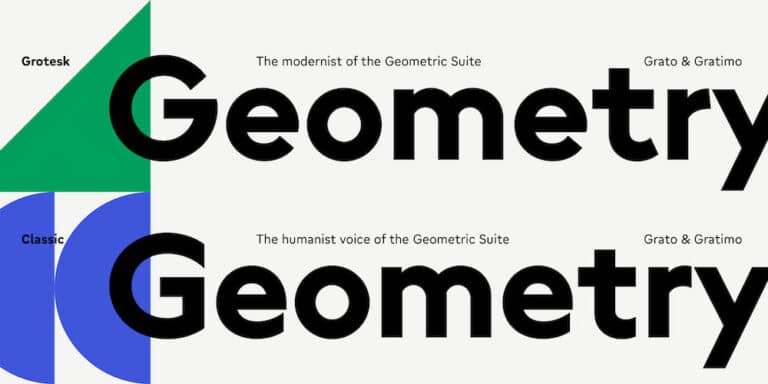
Grato und Gratimo: Serifenlose Großfamilie
Neu bei der Foundry TypeMates ist die Geometric Collection, ein System von Schriften, die durch eine grundlegende Geometrie miteinander vereint sind, sich in ihrem Stil und ihrer Funktion aber unterscheiden.
Jakob Runge und Mona Franz gestalteten vier Schriftfamiien, die durch grafische Klarheit vereint sind. Ausgangspunkt für alle Familien bildet der geometrische Kern der Grato. Durch stilistische Variationen in den Strichenden und Großbuchstaben entwickelten sie davon ausgehend gleich zwei Schriften: eine Grotesk und eine Classic. Diese gleichen sich zwar im Kern, variieren allerdings in der Ausführung und im Erscheinungsbild. Für ein effizientes Arbeiten wurden diese für Text- und Interface-Projektet zusätzlich neu gezeichnet. Das Ergebnis: Gratimo Grotesk und Gratimo Classic.
Grato und Gratimo Grotesk — klare, geometrische Sans mit Faible für Minimalismus.
Grato Grotesk ist der Minimalist in der Geometric Collection: Eine Schrift mit halb geöffneten Stricheneden und flachen Spitzen, die sich durch ihre klare und zeitgenössische Ästhetik auszeichnet – aber auch durch eine charmante Eigenwilligkeit und eine freundliche Ausstrahlung. Der puristische Aufbau schafft Persönlichkeit: einfache Formen, minimaler Strichstärkenwechsel, deutliche Kanten der Bögen zum Stamm sowie rechteckige Punkte, die im Kontrast zu den nahezu perfekten Kreisformen stehen.
Grato Grotesk eignet sich vor allem für Corporate Designs und Layouts, die mit einer großen Schriftfamilie ein klares und warmes Erscheinungsbild kreieren wollen. Mit insgesamt neun Schnitten bietet die Grato Grotesk ein breites Spektrum von hauchdünnen Hairlines bis hin zu maximal dunklen Black-Schnitten.
Grato Grotesk spricht mehr als 270 Sprachen, verfügt über hoch- und tiefgestellte Ziffern, Brüche sowie Text- und Versalziffern in proportionaler sowie tabellarischer Breite. Außerdem gibt es ein paar stilistische Alternativen, mit denen sich das Schriftbild individuell anpassen lässt.
Bei der Entwicklung der Schrift setzte TypeMates bewusst auf geometrische Formen und verzichtete auf kalligrafische Aspekte.
Die Grotesk ist in zwei optischen Größen verfügbar: Während sich die Grato Grotesk perfekt für CI und Layout eignet, sorgt die Gratimo Grotesk in sechs Strichstärken plus Italiens und mit optimierter Lesbarkeit bei Text- und UI-Projekten für weitere Einsatzmöglichkeiten.
Grato und Gratimo Classic — eine humanistische Sans mit Liebe zur Geometrie.
Grato Classic ist das humanistische Mitglied in der Geometric Collection. Mit vertikalen Strichenden, deutlichen Spitzen und einer klaren geometrischen Grundform wirkt die Sans zeitlos wie puristisch und versprüht dabei einen Hauch von Eleganz. Der Aufbau schafft Charakter: klare Formen, minimalen Strichstärkenwechsel, deutliche Kanten der Bögen im Übergang zum Stamm und ebenfalls rechteckige Punkte.
Grato Classic bietet sich insbesondere für Corporate Designs und Layouts an, die mit einer vielseitigen Schriftfamilie ein stilvolles und zugleich klares Erscheinungsbild kreieren wollen. Eine Sans für alle Marken, denen sprachliche Vielfalt und eine saubere Bildschirmdarstellung am Herzen liegt.
Auch Grato Classic verfügt über neun Strichstärken von Hairline bis Black und unterstützt mit dem lateinischen, kyrillischen und griechischen Schriftsystem sowie vietnamesischen Akzenten ebenfalls mehr als 270 Sprachen.
Die schlichten, puristischen Formen, die einerseits modern und minimalistisch wirken, versprühen gleichzeitig aber auch einen gewissen Vintage-Charme, was uns an Zeiten erinnert, in denen Schriften durch ungeschliffene Macken und Unvollkommenheit geprägt waren.
Auch Grato Classic gibt es in zwei optischen Größen: Gratimo Classic zeichnet sich mit sechs Schnitten plus Italiens durch weniger Geometrie und mehr Lesbarkeit in kleinen Punktgrößen aus.
Während Grato (jeweils oben) Wert auf pure Geometrie legt, liegt der Fokus von Gratimo auf der praktischen Anwendung.